유럽 타이포그라피의 재발견 – 타이포그래피 매거진의 진수, Baseline
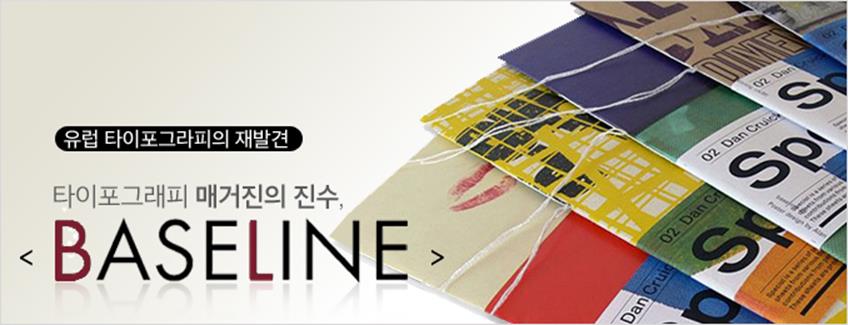
지난 영국 타이포그래피 기행에 이어 현대 타이포그래피 매거진의 진수인 <Baseline>에 대한 이야기로 시작해 글꼴 디자인 교육의 메카인 레딩대학교(University of Reading)과 최근 영국에서 가장 영향력 있는 폰트전문 디자인회사 중 하나인 달튼맥(Dalton Maag Font Foundry)를 방문해 실시했던 워크숍 중심으로 3회에 걸쳐 연재할 예정이다. 앞서 언급한 학교와 스튜디오 방문을 중심으로 한 칼럼은 최근 영국 타이포그래피와 서체 디자인 현장 상황과 그들의 철학을 파헤쳐보는 대담 형식으로 게재하고자 한다.
김창식: 많은 이들이 당신의 <Baseline> 매거진을 잘 알고 있지만, 폰트클럽 독자들을 위해 간단한 소개를 부탁할게요.
한스: 폰트클럽 여러분과 만나게 되어 반갑습니다. 저는 한스 디히터(Hans Dieter Reichert)라고 합니다. 현재 영국 캔드(Kent)에서 디자인 회사 HDR Visual Communication과 출판사 Bradbourne Publishing을 운영하고 있습니다. 그리고 타이포그래피 전문 잡지인 <Baseline>의 편집인 겸 아트디렉터로 활동을 겸하고 있습니다. 디자이너로서의 경력은 활자 조판공으로 독일에서 3년 간의 전문인 과정을 거치면서 시작했습니다. 이후에 에센 대학교(University of Duisburg Essen)에서 Lazlo Lakner과 Hans Nienheysen, 그리고 Willy Fleckhaus 교수님으로부터 시각디자인을 공부했습니다. 또 스위스 바젤의 Kunstgewerbe Design School과 영국의 London University of the Arts(LCC)에서 수학하기도 했습니다. 서유럽 전역을 돌며 디자인 공부를 하다 네덜란드 암스테르담에 있는 디자인회사 BRS maatschap van vormgevers과 TD Total Design에서 몇 년간 활동하였고 마침내 런던에 소재한 국제적인 디자인 그룹인 Banks & Miles (런던, 함부르크, 그리고 벨기에 브리셀에도 지사가 있는)에 입사하여, 한 5년간 더욱더 깊이 있는 디자인 활동을 할 수 있었죠.
마침내 1992년에 제 이름을 건 디자인회사(HDR design)를 설립하게 되었습니다. 주로 기업과 출판사들이 제 클라이언트였고요. 1994년에는 Bradbourne Publishing이라는 출판사를 동업자와 함께 설립하기에 이르렀습니다. 당시 지표를 잃고 있던 Lettraset 회사의 사외보 형식 잡지였던 <Baseline>을 국제적인 타이포그래피 잡지로 계속해서 이끌어 갈 목표를 갖고 있었습니다. 그간에 수많은 출판물 디자인과 타이포그래피 실험을 계속해 왔고 영국의 많은 디자인 관련 학교에서 강의와 특별 워크숍 그리고 학교 발전 자문위원으로 활동했습니다. 2003년에는 AGI에 초청받아 회원으로 활동해 오다가 2006년에는 University for the Creative Arts(UCA)로부터 명예 학위를 수여 받기도 했죠.
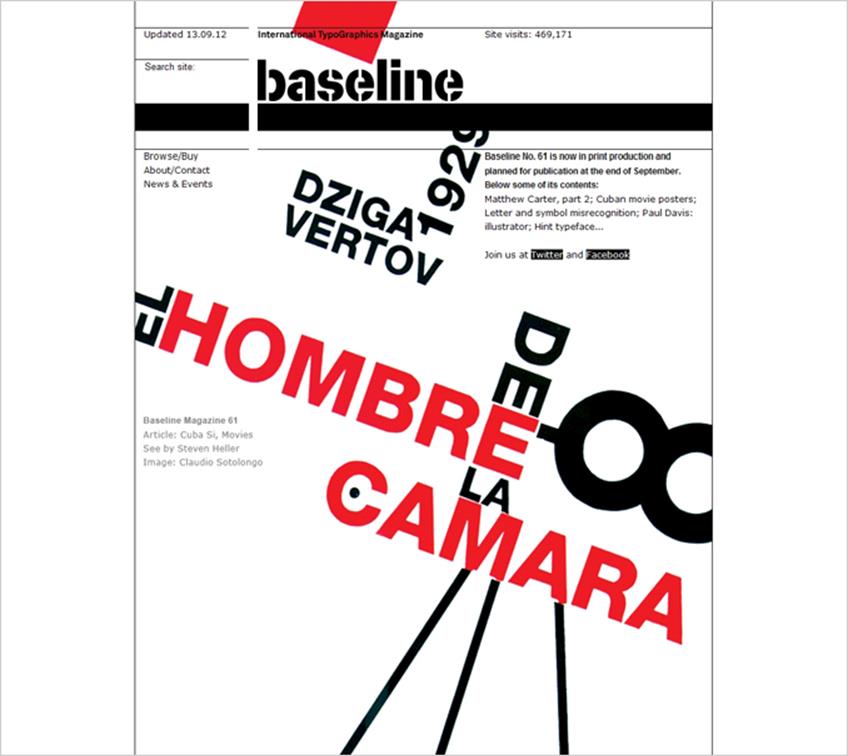
베이스라인 웹사이트(www.baselinemagazine.com)
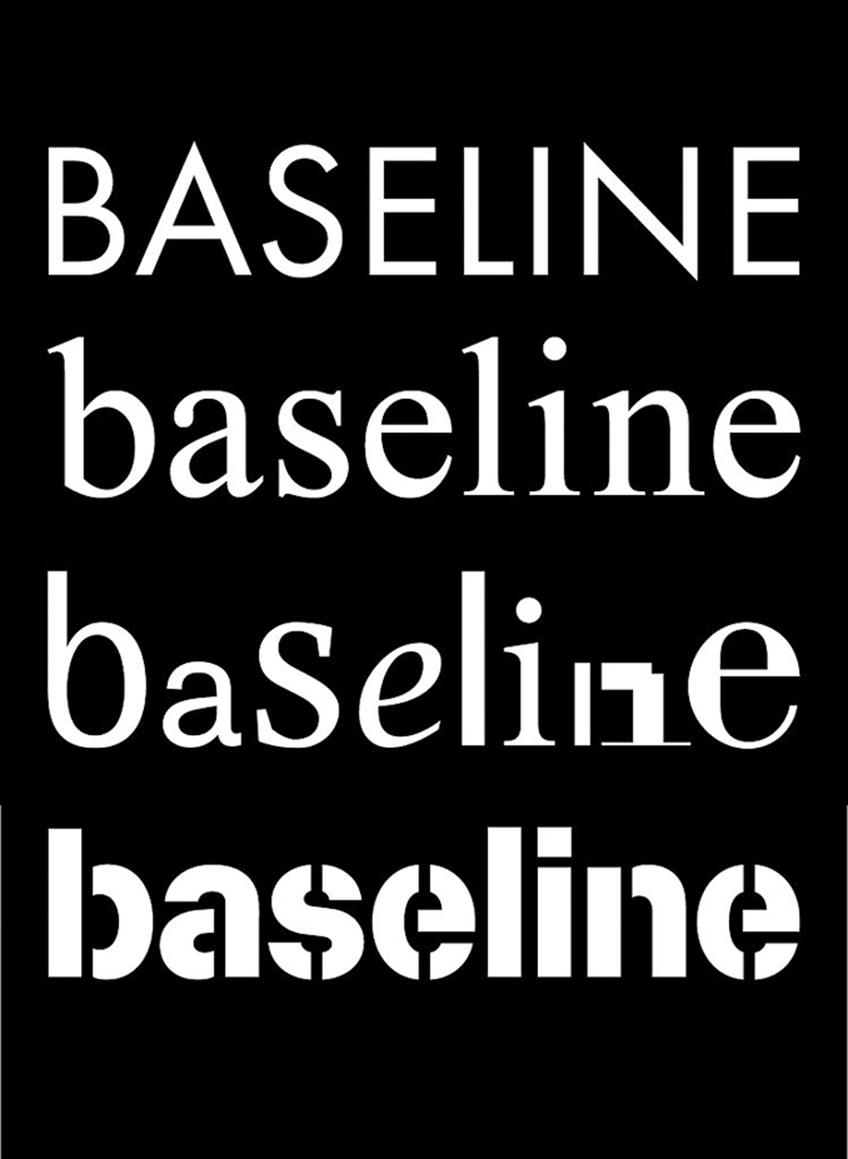
베이스라인 잡지의 제호의 변천사(위에서부터 초기 제호)
<Baseline> 매거진 발행인이자, 편집인 그리고 아트디렉터인 한스 디히터
HDR 비주얼 커뮤니케이션 디자인회사의 내부전경과 팀원들
HDR 비주얼 커뮤니케이션 디자인 회사와 <Baseline>을 발행하는 브래드보우른 출판사가 있는 보우른 하우스(Bradbourne House)
김창식: 지금까지 가장 큰 영향을 준 인물은 누구인가요? 그리고 최근에 감명을 받았거나 존경하는 작가가 있으면 소개해주세요.
한스: 제게 영향을 준 분은 제 멘토였던 독일 교수님 빌리 Willy Fleckhaus와 Lazlo Lakner, 그리고 영국인 교수님 Brian Grimbley입니다. Fleckhaus 교수님은 언제 봐도 탁월하고 강렬한 인상의 타이포그래피와 일러스트레이션 그리고 사진 작품들을 선보이셨죠. 그 엄청난 열정과 자신감 넘치는 에너지에 감명을 받았습니다. 아시다시피 Fleckhaus 교수님은 12칼럼 그리드의 혁신으로 잘 알려진 <Twen> 매거진 디자인을 통해 1960년대에 반향을 불러일으킨 장본인이기도 하죠.
반면에 Lakner 교수님은 다분히 예술적이고, 서정적이며 시적이신 분이에요. 섬세한 아름다움의 타이포그래피와 인포메이션 디자인의 매력이 제 영감을 자극했습니다. 그리고 Grimbley 교수님은 감각적이면서도 인간적이고, 한편으론 굉장히 논리적이며 분석적인 타이포그래피 미학을 가르쳐 주셨습니다. 감사하게도 이 세분 덕분에 각기 다르면서도 일맥상통하는 타이포그래피 진가를 다 어우를 수 있었죠. 전문 디자이너 중에서는 당연히 Alan Fletcher, Josef Muller-Brockmann, Helmut Schmid, 그리고 Otl Aicher를 꼽을 수 있습니다. 전형적인 현대 독일 그래픽디자인의 근간을 이룬 대가들이죠.
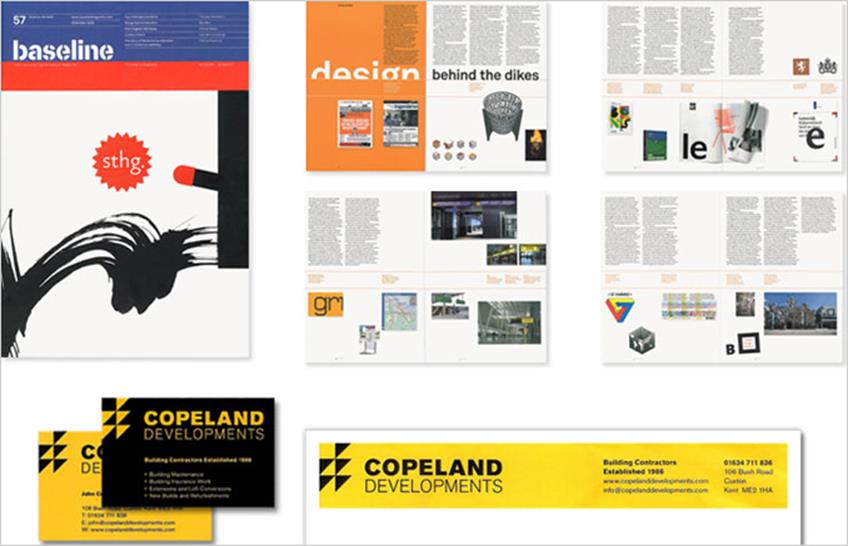
HDR 디자인 회사의 포트폴리오
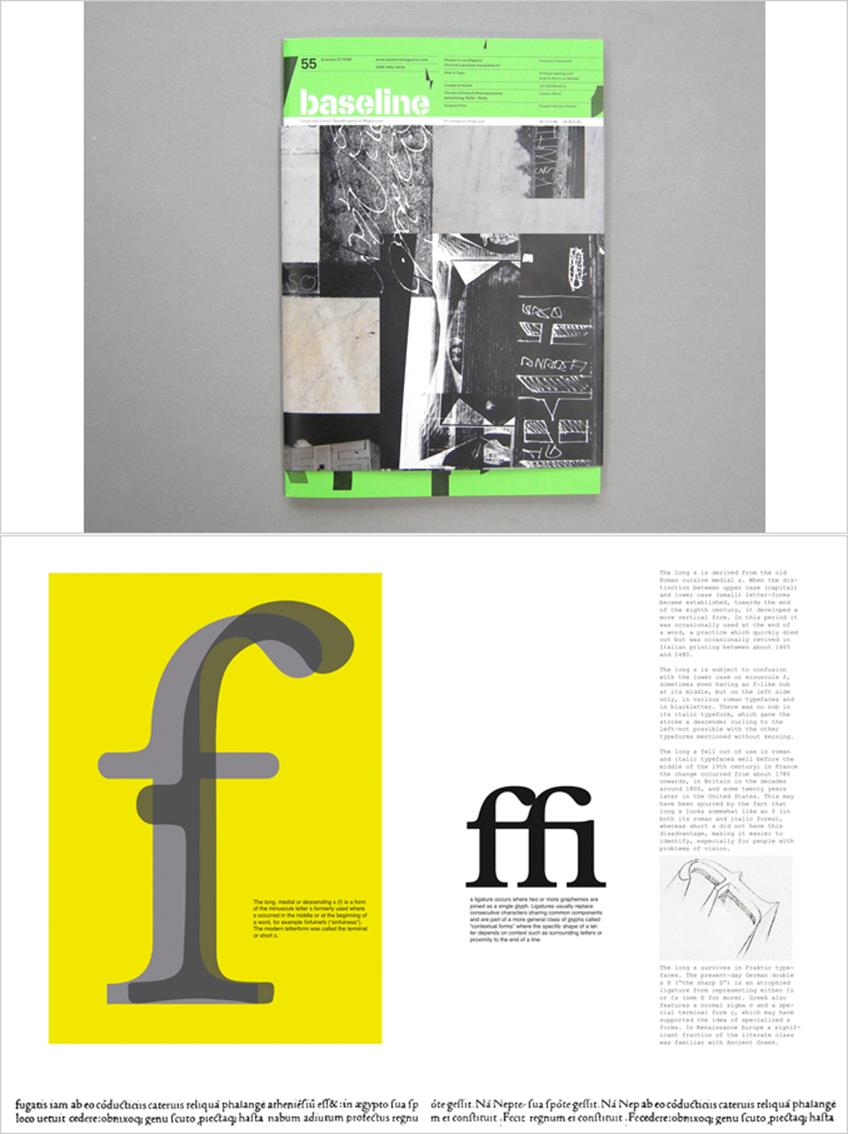
<Baseline> 매거진 표지 및 내지
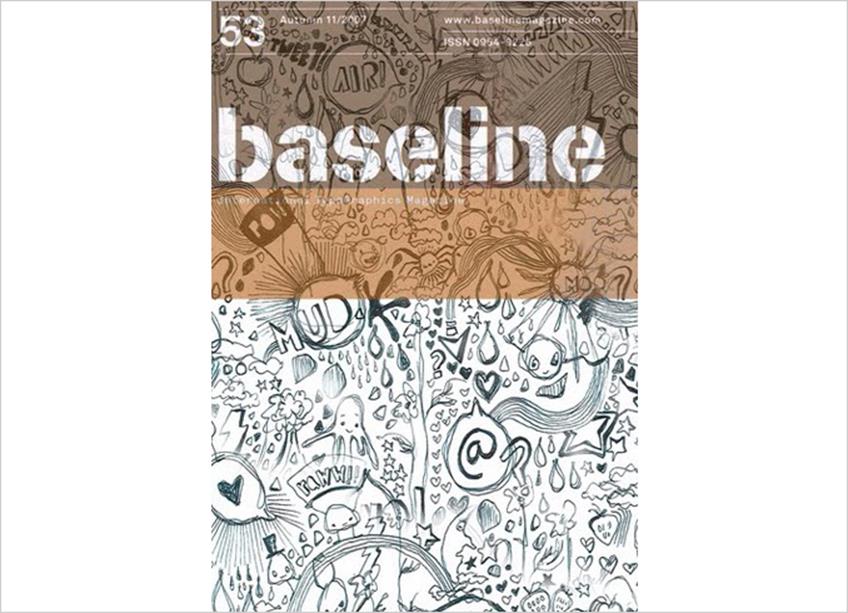
<Baseline> 매거진 53호 표지
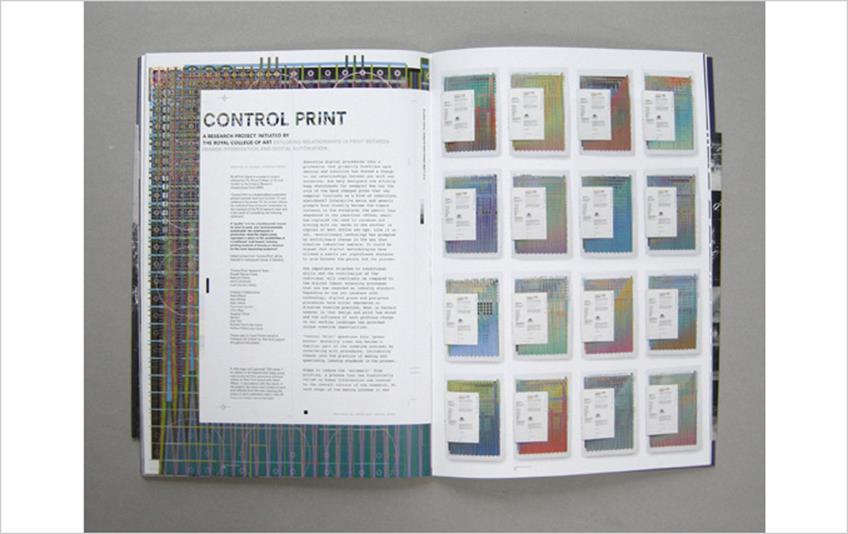
<Baseline> 매거진 프린트 프로덕션 특집기사
<Baseline> 매거진 폴 랜드 특집기사. 표지 및 내지 펼침면
12칼럼 그리드의 혁신으로 잘 알려진 Willy Fleckhaus의 <Twen> 매거진.
이 잡지는 1960년대 당시로서는 혁신적인 포맷으로 잡지 디자인계에 반향을 불러일으켰다.
Lazlo Lakner의 캘리그라피 습작들
김창식: <Baseline> 매거진만의 스타일이 있다면 어떻게 정의할 수 있을까요?
한스: <Baseline> 매거진은 각 장이 매우 독립적인 내용으로 구성되어있습니다. 그리고 내지에서부터 디자인의 컨셉트를 추출해 표지로 이어지는 디자인 접근 방식도 한 몫하고 있죠. 저는 컨텐츠를 만드는 저자 못지않게 뚜렷한 철학과 소신을 지닌 디자이너가 일련의 창작 과정과 그 행위의 주요 부분을 담당하는 핵심이라고 생각합니다. 물론 편집인이나, 인쇄 및 관련 전문가들의 총체적인 노력이 함께 이루어질 때 그 빛이 더욱더 발하는 건 두말할 나위 없겠죠.
저와 함께 일하는 디자이너들은 컨텐츠를 충분히 숙지하고 이해하는 범주를 넘어서 그 안에 숨어있는 깊은 맛을 찾아내어 타이포그래피와 이미지들로 재구성해 냅니다. 지적이고도 감각적인 일련의 과정을 통해 새로운 시각물을 창출해 내는 막중한 임무를 맡고 있습니다. 편집디자이너로서 저는 주어진 컨텐츠 안에 이미 그 디자인에 필요한 컨셉트와 핵심이 녹아있다고 생각합니다. 다만 어떻게 이것을 찾아내고 시각적으로 재해석하여 새롭고도 효과적으로 드러낼 수 있는지가 핵심 문제인 것입니다.
<Baseline> 매거진은 예나 지금이나 각 장의 글에 대한 특징이 최대한 발현되도록 독립적이고도 독특한 방식으로 디자인합니다. 전체적인 틀에 너무 구속되지도 않고 적당히 타협해 응용하는 상투적인 편집디자인 레이아웃은 거부합니다. 개성을 십분 돋보이게 하는 데에 초점을 맞추고 있죠.
김창식: 무엇이 <Baseline> 매거진을 그렇게 오랜 기간 유명하고 독보적인 존재로 자리매김 할 수 있게 한 것일까요?
한스: <Baseline>은 1979년에 전사 사식(판박이 식의 전사용 글꼴 필름)으로 그래픽 디자인계에 한동안 혁명을 일으켰던 Letraset라는 회사에서 홍보용으로 만든 사외보로 출발했습니다. 그때부터 <Baseline> 매거진은 타이포그래피 매거진 분야에서 주도적인 역할을 해왔죠. 상당한 영향력을 유지해올 수 있었던 주된 이유는 잡지 컨텐츠가 타이포그래피의 가장 근본적이고 원리적인 이슈들을 깊이 있게 다루어왔기 때문이다.
1980년대 말로 접어들면서 최신 컴퓨터를 비롯한 신기술이 등장하면서 Letraset는 시대 변화에 발 빠르게 대처하지 못했습니다. 자사 제품을 중심으로 한 타이포그래피 컨텐츠에서 다양한 영역으로의 확대와 그에 부응하는 변화가 필요했고 당연히 새로운 편집인과 아트디렉터가 필요했죠. 그 시점에서 <Baseline>은 다시 한번 새로운 변화를 맞이하게 됩니다. 지금에 이르기까지 더욱 더 그 영역을 넓혀 다방면의 타이포그래피 세계를 다루는 잡지로 거듭나게 된 것이죠. 지금도 1년에 약 3회 정도 발행하고 있습니다. 엄선된 주제와 사례를 중심으로 매 호 혁신적인 디자인을 선보여왔던 것이 <Baseline>을 독보적인 존재로 오랜 시간 유지하게 해준 요인이 아닐까요?
<Baseline> 매거진 53호 표지와 커버. 잡지 상단의 푸른 보라색 수평선 아래 부분은 의도적으로 제작된 포스터 겸용의 커버이다. 커버를 벗겨 펼치면 포스터가 되는 형식)으로 2008년 베이징 올림픽에 관한 내용을 담고 있다
<Baseline> 매거진 53호 내지 펼침면. 2008년 베이징 올림픽에 참여한 왕민 디자이너와의 인터뷰 내용을 담고 있다.
<Baseline> 매거진 59호 표지와 커버. 53호와 같은 형식으로 ‘디자인에 있어서 단순성’이라는 주제하에 세계적인 디자이너들의 명언집으로 엮었다.
<Baseline> 매거진 59호 내지 펼침. 다양한 그리드의 활용을 보여주는 한 예이자 여러 훌륭한 잡지 디지인의 사례에 대한 논평을 담고 있다
김창식: 작업들 중에 가장 성공적이었고 애착이 가는 프로젝트를 꼽아볼 수 있을까요?
한스: 제 디자인 회사인 HDR Visual Communication을 통해 그간 수많은 작업을 해왔습니다. 기억에 남는 몇 가지 작업 중에는 Waldorf 유치원의 아이덴티디 및 종합적인 디자인 시스템을 구축하는 프로젝트와 국제 금융 회사들의 온라인 리서치 프로젝트가 있습니다. 국제적인 디자인, 예술 문화 출판사인 Phaidon의 시리즈 ’20세기 위대한 디자이너 전기 시리즈'(Paul Rand, Max Huber, Otl Aicher, Alexey Brodovitch 등의 생애를 심층 조명하고 그 모든 작업을 총망라한 기념 서적들)의 편집디자인을 총괄 제작하였는데, 상당한 방향을 불러일으키기도 했죠. Photo Books Vol. 1+2와 Merz to Emigre의 특별 출판물 디자인도 애착이 가는 작품들입니다.